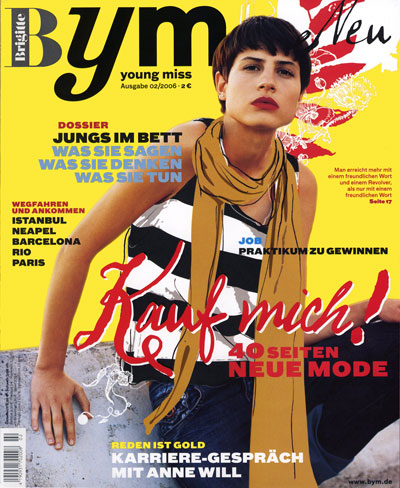
Noch ein Argument für SchreibschriftenDie Erstausgabe von bym ist da (Brigitte Young Miss, Guner +
Jahr): ziemlich frech gestaltet, sehr nett. Auf einem matten Titel macht die
Leser ein hochglänzendes »Kauf mich!« an, gesetzt aus der frechen
Schreibschrift FF Pepe. Auch im Inneren des Magazins spielt sie als
Auszeichnungsschrift eine tragende Rolle, neben Sauna von
Underware und Renault von E+F. Was kaum jemand weiß: Andy
Der spanische Designer Pepe Gimeno entwarf seine FF Pepe (probesetzen) 2002 nach einer Vorlage, die er in
einem alten Langspielplatten-Archiv fand: das Cover einer Lesung von Tennessee
Williams aus dem Jahre 1952. Allerdings ist sich die Fachwelt nicht ganz im
klaren darüber, ob Andy die Kringelbuchstaben selbst zu Papier brachte oder
seine Mutter Julia Warhola schreiben ließ, die in der frühen Phase
seines Künstlerdaseins öfters für ihn zur Feder griff (siehe
Wikipedia).